싸인은 단순한 이름을 적는 것이 아니라, 개성과 스타일을 표현하는 중요한 요소예요. 특별한 기호를 추가하면 싸인이 더 독창적이고 세련돼 보일 수 있어요! 😆 그럼 싸인에 넣으면 좋은 5가지 특별한 기호를 알아볼까요? 🚀
싸인에 기호를 넣으면 좋은 이유 🔍
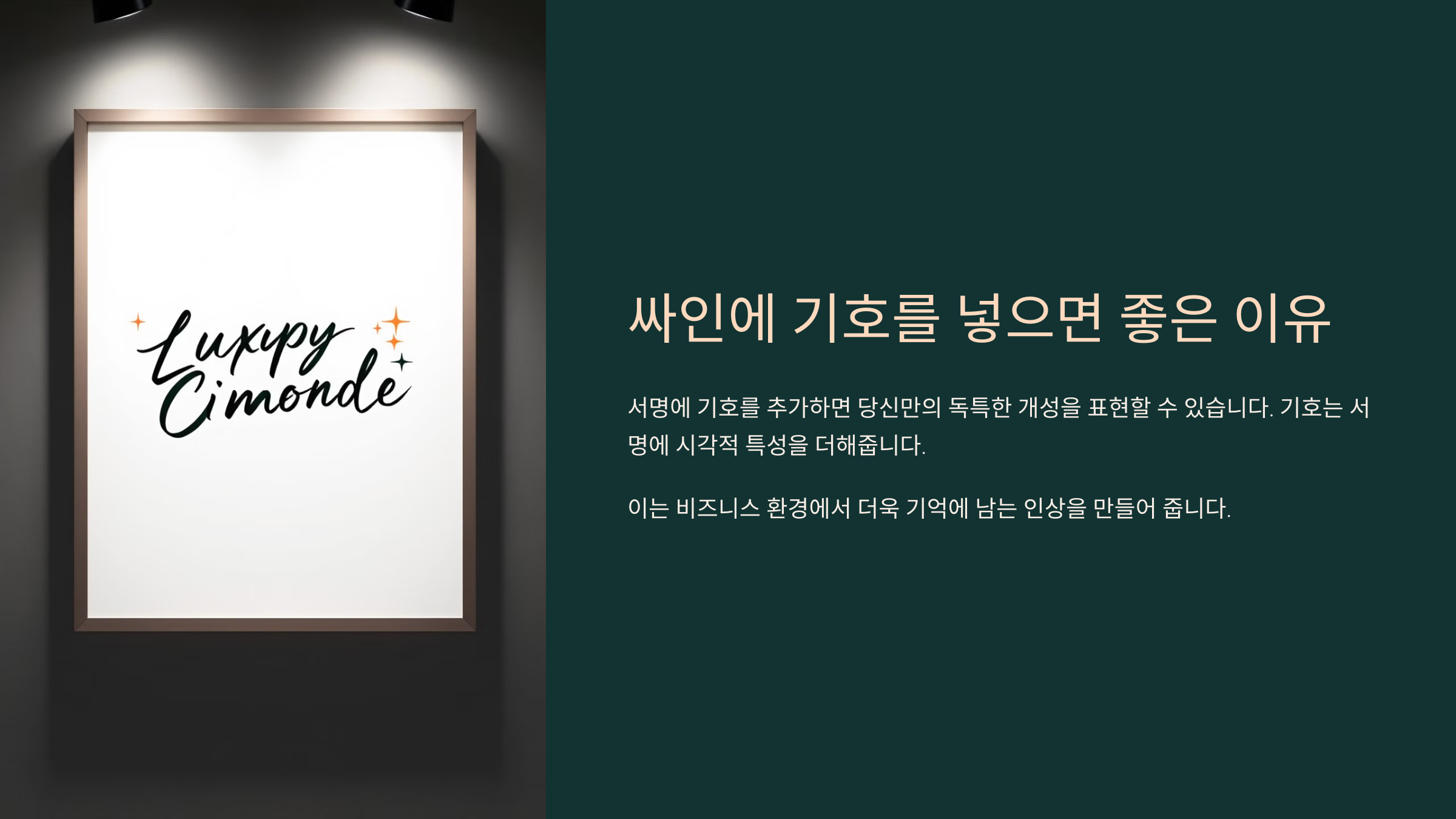
싸인에 기호를 추가하면 심플하면서도 강렬한 인상을 줄 수 있어요. 너무 흔한 싸인 대신, 나만의 개성을 살릴 수 있는 디자인을 만들 수 있죠. 그럼 싸인에 기호를 넣으면 어떤 장점이 있을까요? 🤔
📌 싸인에 기호를 넣는 장점 💡
장점 설명 개성 표현 기호를 추가하면 싸인이 더 독창적이고 차별화돼요. 디자인 강화 특별한 포인트가 되어 싸인이 더 세련돼 보일 수 있어요. 가독성 증가 싸인의 끝을 강조하거나 균형을 맞출 수 있어요. 기억하기 쉬움 특징적인 기호가 있으면 상대방이 쉽게 기억할 수 있어요. 이제 싸인에 넣으면 좋은 5가지 특별한 기호를 하나씩 알아볼까요? 😆
⭐ 별 기호: 특별한 포인트
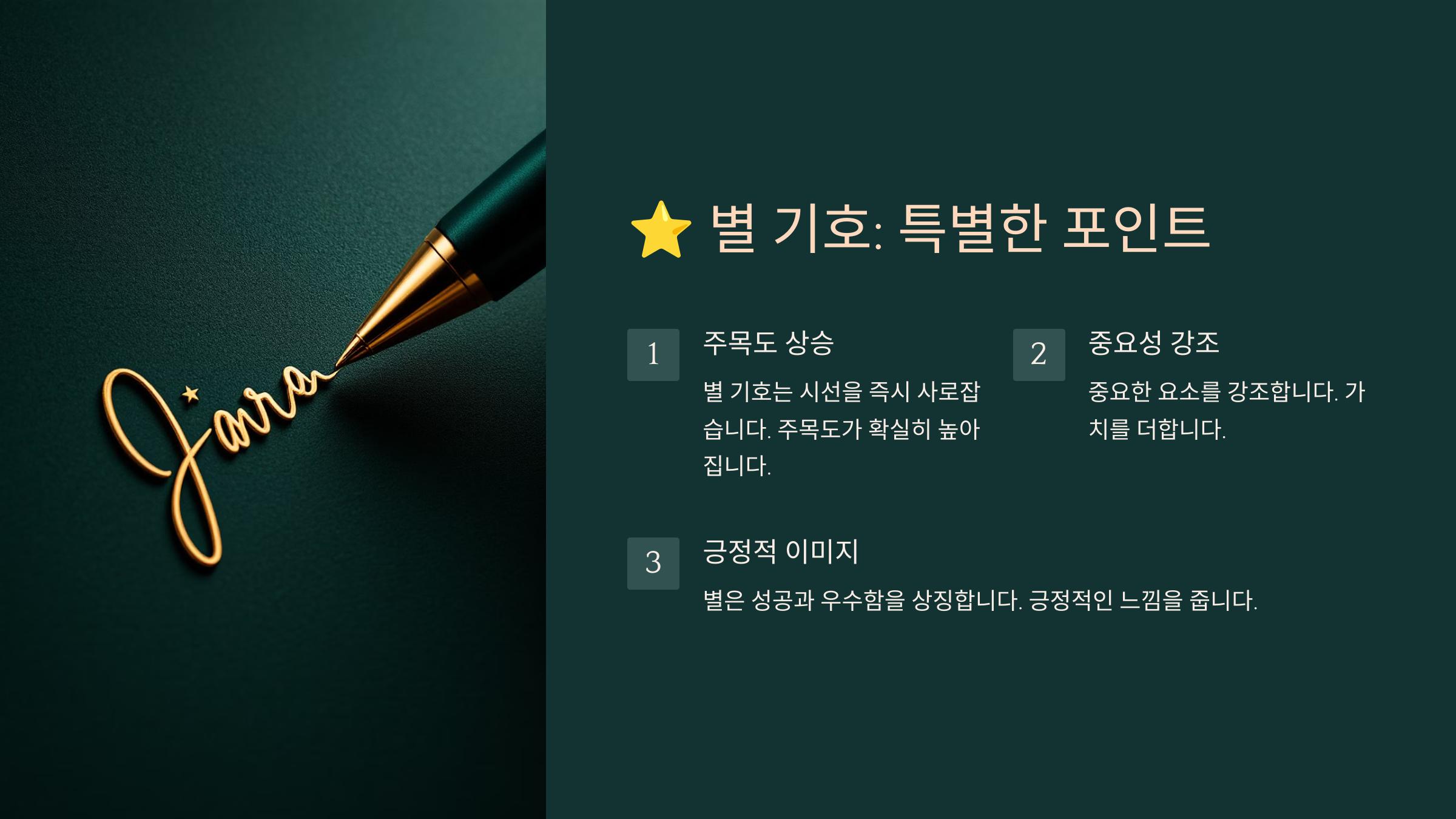
별 기호(⭐)는 싸인에 개성을 더하고 특별한 느낌을 주는 대표적인 기호예요. 많은 연예인과 유명 인사들이 싸인 끝에 별을 추가해 스타일을 완성하죠! ✨
🌟 별 기호를 활용하는 3가지 방법
- ⭐ 싸인의 끝에 작은 별을 추가해 개성을 살린다.
- ⭐ 이니셜과 함께 사용해 독창적인 디자인을 만든다.
- ⭐ 별 크기를 조절해 세련된 느낌을 연출한다.
별 기호는 밝고 긍정적인 이미지를 줄 수 있어요. 그럼 밑줄(__)을 활용한 싸인 디자인도 알아볼까요? 😆
__ 밑줄: 강렬한 강조
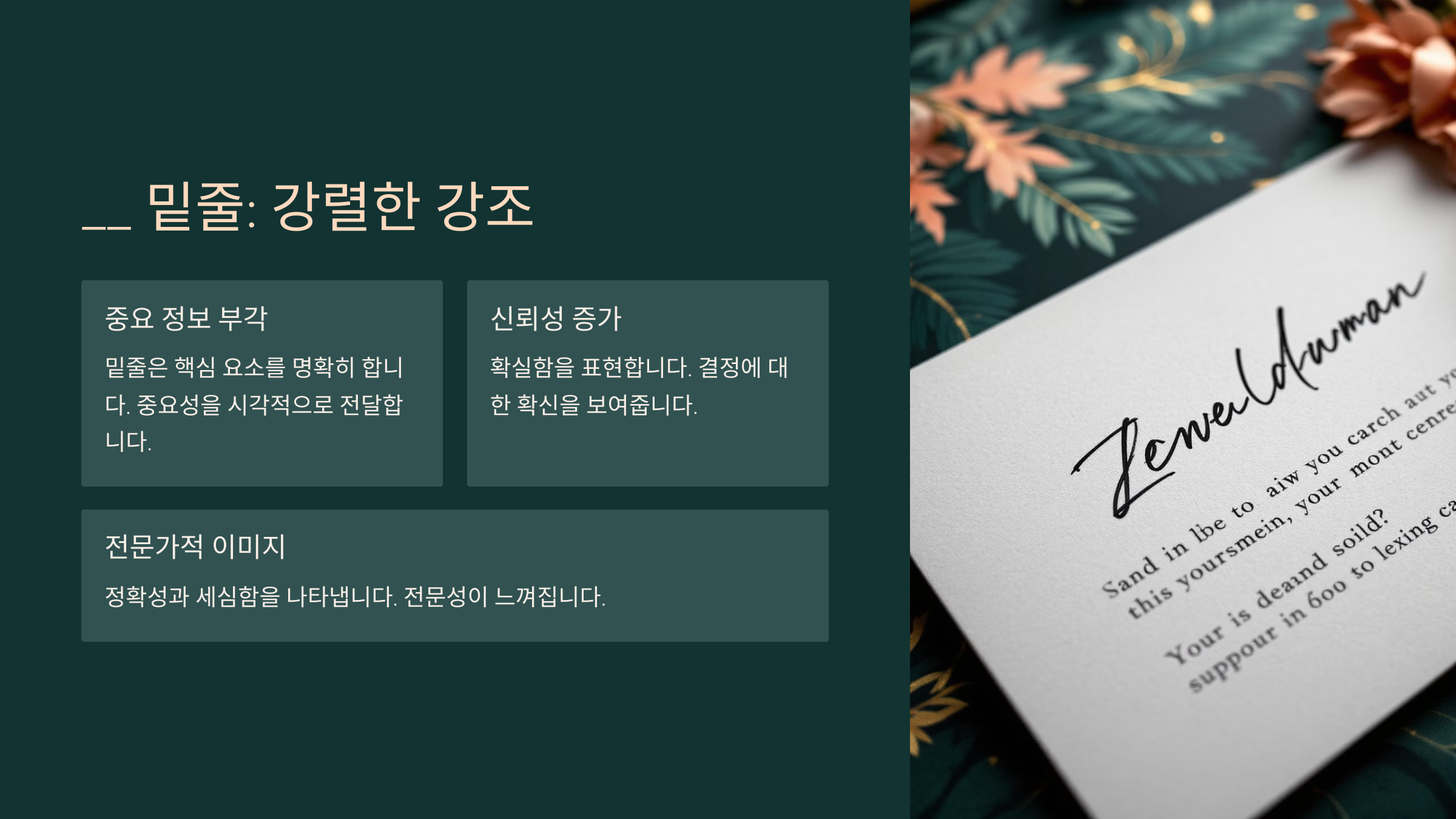
밑줄(__)은 싸인의 중요한 부분을 강조하는 효과가 있어요. 특히 싸인의 마지막 부분에 밑줄을 긋는 경우가 많아요. 🖊
📌 밑줄을 활용하는 3가지 방법
- ⏤ 싸인의 끝에 밑줄을 추가해 강렬한 마무리를 한다.
- ⏤ 이름의 특정 글자 아래 밑줄을 긋는다.
- ⏤ 두 줄 밑줄(⏤⏤)을 넣어 특별한 스타일을 만든다.
밑줄을 사용하면 싸인이 더 강렬하고 힘 있어 보이는 효과가 있어요! 그럼 싸인의 디테일을 살려주는 점(•) 기호도 알아볼까요? 🔍
• 점: 세련된 마무리
점(•) 기호는 싸인의 끝에 넣으면 깔끔하고 세련된 느낌을 줘요. 작은 변화지만 싸인의 밸런스를 맞추는 데 효과적이랍니다! 🎯🎨 점 기호를 활용하는 3가지 방법
- • 싸인의 끝에 점을 찍어 정리된 느낌을 준다.
- • 두 개의 점(..)을 활용해 개성을 살린다.
- • 점을 곡선처럼 배치해 스타일을 연출한다.
점 기호는 단순하지만 싸인을 완성하는 중요한 요소가 될 수 있어요. 그럼 싸인에 역동적인 느낌을 줄 수 있는 화살표(↗)도 살펴볼까요? 😆
↗ 화살표: 역동적인 느낌
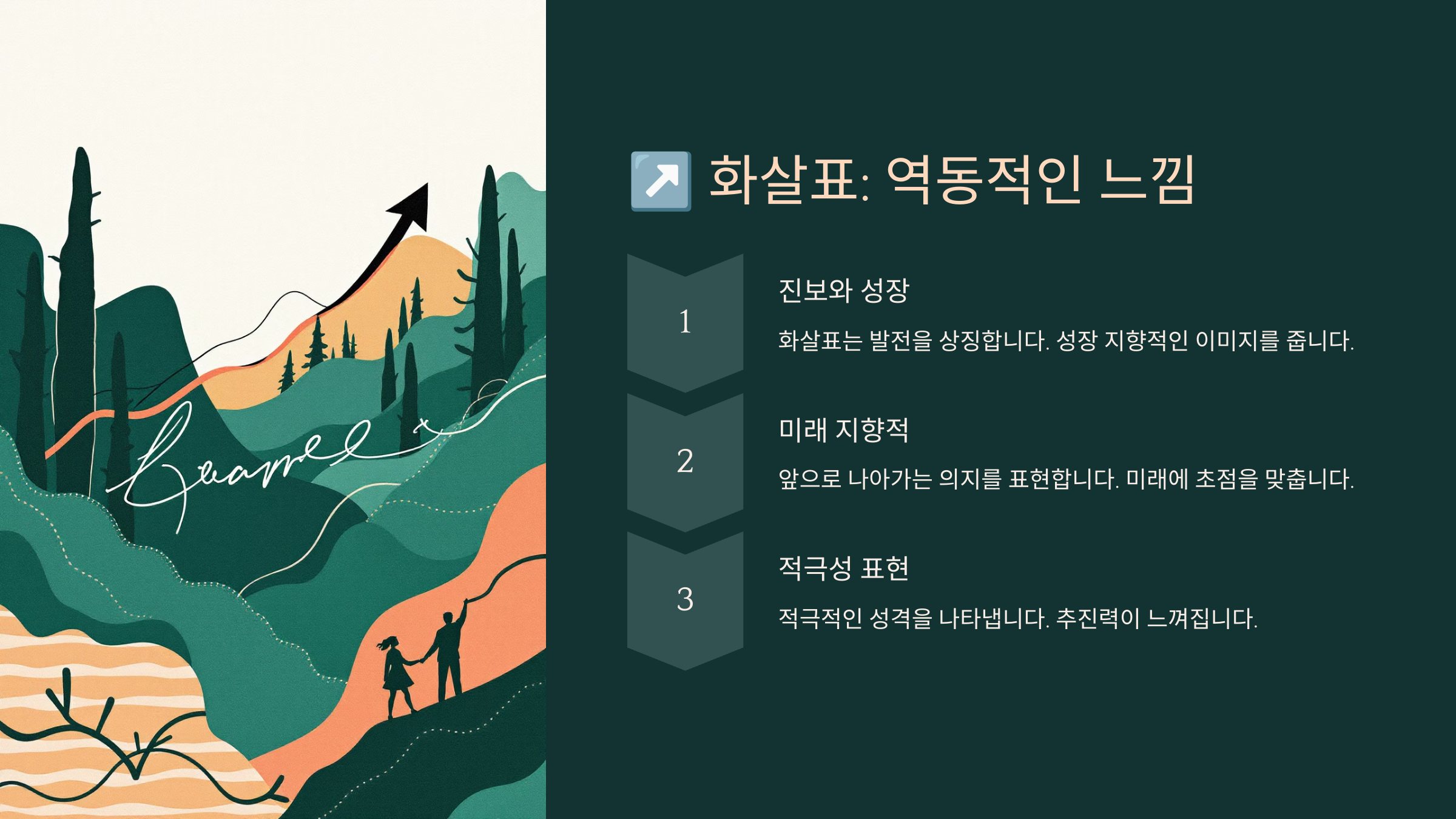
화살표(↗)는 성장과 상승하는 이미지를 담을 수 있는 기호예요. 싸인에 화살표를 넣으면 더 역동적인 느낌을 줄 수 있죠! 🚀
⚡ 화살표를 활용하는 3가지 방법
- ↗ 싸인의 끝에 작은 화살표를 넣어 상승하는 느낌을 준다.
- ↗ 이니셜을 강조할 때 활용해 독특한 스타일을 만든다.
- ↗ 기울기를 활용해 자연스럽게 화살표를 연결한다.
화살표를 활용하면 자신감 있고 강한 인상을 남길 수 있어요. 그럼 신뢰감을 주는 체크(✔) 기호도 활용해 볼까요? 😊
✔ 체크: 신뢰와 완벽함
체크(✔) 기호는 성공, 신뢰, 완벽한 마무리를 의미해요. 싸인에 체크 기호를 넣으면 전문적이고 깔끔한 이미지를 줄 수 있죠! 😎
🔹 체크 기호를 활용하는 3가지 방법
- ✔ 싸인의 마지막에 체크를 추가해 완성도를 높인다.
- ✔ 이니셜과 함께 사용해 독창적인 디자인을 만든다.
- ✔ 기울어진 형태로 스타일을 살린다.
체크 기호를 활용하면 깔끔하고 정리된 느낌의 싸인을 만들 수 있어요! 그럼 마지막으로 싸인 기호와 관련된 FAQ를 살펴볼까요? ❓
FAQ ❓
Q1. 싸인에 기호를 넣으면 어떤 효과가 있나요?
A1. 싸인에 기호를 추가하면 개성이 강해지고, 더 세련된 디자인을 만들 수 있어요. 또한, 기호는 싸인의 가독성을 높이면서도 특별한 느낌을 줄 수 있답니다. ✨
Q2. 싸인에 너무 많은 기호를 넣으면 안 좋을까요?
A2. 네, 기호가 너무 많으면 오히려 복잡해지고 가독성이 떨어질 수 있어요. 기본적으로 한두 개 정도의 포인트 기호만 활용하는 것이 좋아요. ✔
Q3. 싸인에 가장 많이 사용되는 기호는 무엇인가요?
A3. 싸인에 가장 많이 사용되는 기호는 다음과 같아요! - ⭐ 별: 개성을 강조하는 효과 - __ 밑줄: 강렬한 마무리 - • 점: 세련된 느낌 추가 - ↗ 화살표: 상승하는 느낌 연출 - ✔ 체크: 신뢰감과 완벽함 표현 이 기호들은 싸인의 완성도를 높이는 데 유용하답니다! 😆
Q4. 싸인에 기호를 넣을 때 주의해야 할 점은?
A4. 싸인에 기호를 넣을 때는 일관성과 균형을 유지해야 해요. - 너무 크거나 과한 기호는 싸인을 어지럽게 보이게 할 수 있어요. - 적절한 크기와 위치를 고려해 싸인과 잘 어우러지게 배치하세요. 😉
Q5. 싸인에 기호를 넣으면 법적으로 문제될까요?
A5. 아니요! 싸인은 본인의 의도가 반영된 형태라면 문제되지 않아요. 단, 공식 문서에서는 지나치게 복잡한 디자인보다는 깔끔한 싸인이 더 적합할 수 있어요. 📝
Q6. 싸인에 기호를 넣으면 위조 방지 효과가 있나요?
A6. 네, 기호를 활용하면 더 개성 있고 복잡한 디자인이 되므로 위조가 어려워질 수 있어요! 특히 독창적인 기호 조합은 싸인을 더 안전하고 고유하게 만들어줘요. 🔒
Q7. 싸인 기호를 더 창의적으로 활용하는 방법이 있을까요?
A7. 기호를 단순히 추가하는 것뿐만 아니라 싸인과 자연스럽게 연결하면 더욱 창의적으로 보일 수 있어요! 예를 들어, - 별(⭐)을 마지막 획과 연결하면 유니크한 디자인이 돼요. - 화살표(↗)를 이니셜과 조합하면 개성 있는 스타일이 완성돼요. - 체크(✔)를 마무리 선과 연결하면 더 자연스럽고 깔끔한 느낌을 줄 수 있어요. 🎨
Q8. 싸인에 넣을 기호를 직접 디자인해도 될까요?
A8. 물론이죠! 기존의 기호를 변형하거나 나만의 심볼을 만들면 더욱 특별한 싸인이 될 수 있어요. 자신만의 기호를 만들어 싸인에 녹여보세요! 😍
📌 마무리
싸인에 기호를 넣으면 더 개성 있고 멋진 스타일을 완성할 수 있어요. 하지만 너무 과하지 않게 적절한 포인트만 추가하는 것이 중요하죠. 자신만의 싸인에 맞는 기호를 찾아 더 독창적인 디자인을 만들어보세요! 🚀